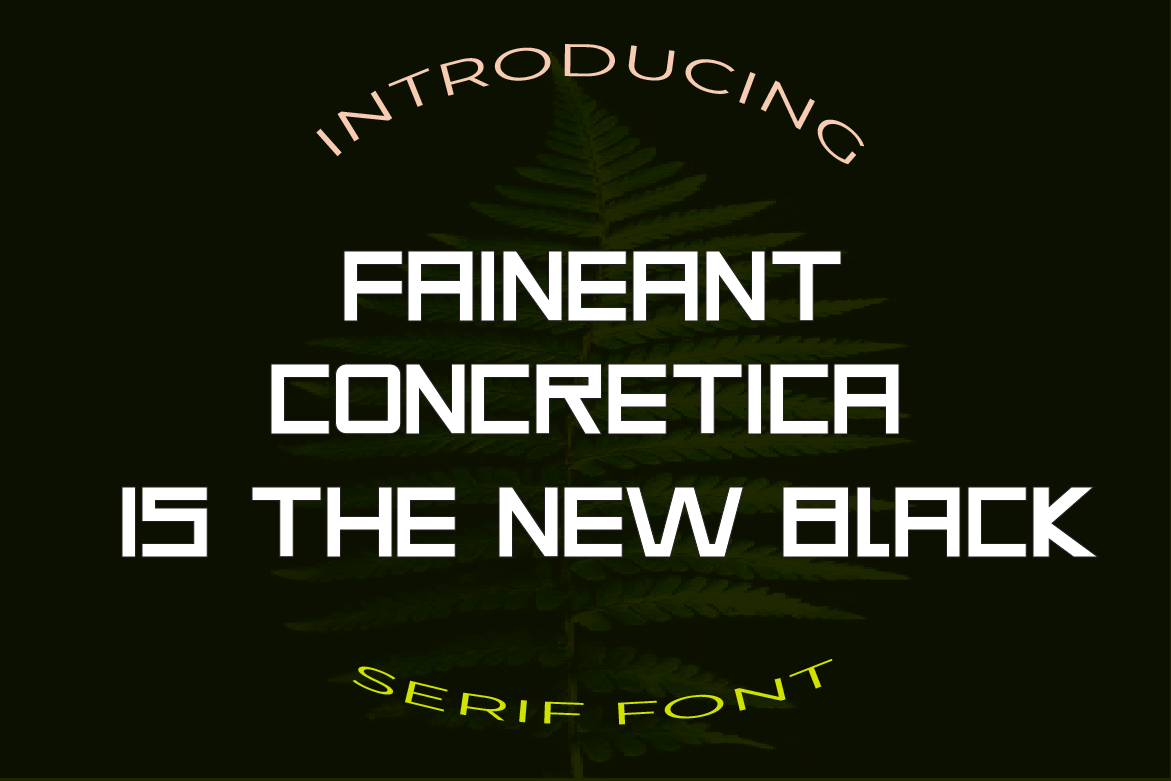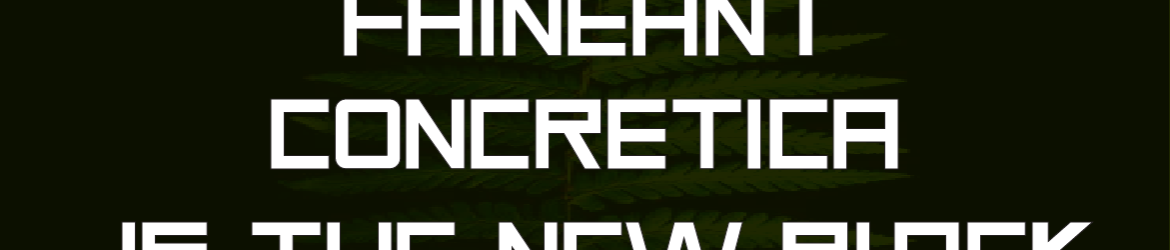
A Faineant Font é uma elegante tipografia serifada que se destaca por seu estilo sofisticado. Perfeita para diversas aplicações onde a estética artesanal adquire um toque atraente, ela se torna ainda mais versátil ao combinar-se com cores vibrantes e brilhantes. Essa fonte é uma invenção refinada que lembra o palavrão “amazing”, convidando seus usuários para explorar novas possibilidades no design de layout. Adaptável aos mais diversos estilos gráficos, a Faineant Font oferece uma experiência visual única e sofisticada, tornando-a um recurso indispensável para criadores de materiais digitais.